แบบอักษรลิขสิทธิ์ฟรีที่ดีที่สุด (2022) – ดาวน์โหลดแบบอักษรฟรีสำหรับใช้ในเชิงพาณิชย์
เผยแพร่แล้ว: 2022-08-27การออกแบบไม่สมบูรณ์หากไม่มีแบบอักษร ทุกแบบอักษรที่คุณเห็นมีบุคลิกที่แตกต่างกัน ที่แบบอักษรหนึ่งอาจแสดงความสง่างามและซับซ้อน แบบอักษรอื่นอาจดูมั่นใจ กล้าหาญ หรือขี้เล่น!
หากคุณกำลังทำงานในโครงการออกแบบ คุณจำเป็นต้องค้นหาแบบอักษรที่เข้ากับบรรยากาศของโครงการของคุณ คุณสามารถหาแบบอักษรดีๆ ได้ทางออนไลน์ แต่ไม่ฟรีสำหรับการใช้งานเชิงพาณิชย์และมีข้อจำกัดด้านลิขสิทธิ์
หลังจากค้นหาแบบอักษรออนไลน์นับพันแบบ แล้ว ฉันพบแบบอักษรฟรีที่ยอดเยี่ยมซึ่งสามารถใช้ในเชิงพาณิชย์ได้ในปี 2022 ในบทความนี้ ฉันจะเปิดเผย 57 แบบอักษรฟรีที่ดีที่สุดสำหรับการใช้งานเชิงพาณิชย์ ใช่ แบบอักษรเหล่านี้ฟรี!!!
แบบอักษรเหล่านี้สามารถใช้กับโลโก้ แบรนด์ ของคุณ โพสต์บนโซเชียลมีเดีย โครงการโรงเรียนและวิทยาลัย บล็อก เว็บไซต์ สื่อการตลาด และแม้แต่ในโครงการของลูกค้า!
ในบทความนี้ ฉันจะช่วยคุณระบุความแตกต่างระหว่างแบบอักษรและแบบอักษร และยังเน้นจุดสำคัญที่คุณควรพิจารณาก่อนเลือกแบบอักษร
สุดท้าย เราจะตรวจสอบหมวดหมู่แบบอักษรที่สำคัญสี่ประเภทและแบบอักษรฟรีที่ดีที่สุดในแต่ละหมวดหมู่ มาดำดิ่งกันเลย!
ข้อควรพิจารณาก่อนเลือกแบบอักษร
ไม่ว่าคุณจะทำงานในโครงการของลูกค้าหรือออกแบบบางอย่างสำหรับตัวคุณเอง สิ่งสำคัญคือต้องไตร่ตรองคำถามต่อไปนี้ก่อนที่จะเลือกแบบอักษร
หมวดหมู่โครงการของคุณคืออะไร?
ประเภทของโครงการออกแบบที่คุณกำลังทำงานอยู่จะเป็นตัวกำหนดบรรยากาศที่คุณต้องการให้แบบอักษรสร้าง
- เป็นคำเชิญงานแต่งงานหรือวันเกิด? แบบอักษร Calligraphic จะเหมาะสำหรับโอกาสนี้
- สำหรับบทความในหนังสือพิมพ์หรือนิตยสาร ฟอนต์ Serif ก็ใช้งานได้ดี
- หากคุณต้องการฟอนต์สำหรับแอพหรือคัดลอกเว็บไซต์ของคุณ Sans Serif จะทำงานอย่างมหัศจรรย์!
ใครคือกลุ่มเป้าหมายของคุณ?
กลุ่มเป้าหมายของคุณยังมีบทบาทสำคัญในการสรุปแบบอักษรของคุณ
ตัวอย่างเช่น เมื่อออกแบบหน้าปกหนังสือสำหรับเด็ก คุณต้องมีแบบอักษรที่ดูเป็นเด็ก ขี้เล่น และไร้กังวล
ในขณะที่โฆษณาแบรนด์กีฬา คุณต้องมีแบบอักษรที่ให้ความรู้สึกที่ชัดเจนและมั่นใจ!
ธีมคืออะไร?
ธีมของโปรเจ็กต์ของคุณจะมีประโยชน์ในการตัดสินใจเลือกแบบอักษรที่คุณสามารถใช้ได้ ตัวอย่างเช่น การใช้แบบอักษรที่น่ากลัวบนการ์ดวาเลนไทน์อาจเป็นความคิดที่แย่มากใช่ไหม
ในการระบุธีมของโครงการ คุณต้องทำความคุ้นเคยและทำความเข้าใจในระดับที่ลึกซึ้งยิ่งขึ้น
ตัวอย่างธีมบางส่วน ได้แก่ ความรัก ความหรูหรา ขี้เล่น มืออาชีพ ลึกลับ สยองขวัญ เป็นต้น
แบบอักษรเทียบกับแบบอักษร
แบบอักษรหมายถึงคอลเล็กชันของแบบอักษรประเภทเดียวกัน ในขณะที่แบบอักษรหมายถึงน้ำหนักและลักษณะของข้อความเดียว
พูดง่ายๆ ก็คือ ชุดของฟอนต์ที่คล้ายกันเรียกว่า แบบอักษร เรียกอีกอย่างว่า Font Family ตัวอย่างเช่น Georgia เป็นแบบอักษรในขณะที่ Georgia Bold, Georgia Italic ฯลฯ เป็นแบบอักษรที่เป็นของมัน
หมวดหมู่แบบอักษรและแบบอักษรฟรีที่ดีที่สุดสำหรับการใช้งานเชิงพาณิชย์
แม้ว่าฟอนต์จะมีการจัดหมวดหมู่มากมาย แต่ก็สามารถจำแนกได้กว้างๆ ได้เป็นสี่ประเภทหลัก – ฟอนต์ Serif, ฟอนต์ Sans Serif, ฟอนต์สคริปต์ และฟอนต์ที่แสดง
ตอนนี้ให้เราพูดถึงแต่ละอย่างในเชิงลึก
แบบอักษร Serif
Serif เป็นแบบอักษรที่เก่าแก่ที่สุดที่เกิดขึ้นในศตวรรษที่ 15 แบบอักษรเหล่านี้มีองค์ประกอบตกแต่งคล้ายเท้าเล็กๆ ที่ด้านบนและด้านล่างเรียกว่า 'Serifs ' ตัวอย่างฟอนต์ Serif ได้แก่ Times New Roman, EB Garamond, Baskerville เป็นต้น
ฟอนต์ Serif โดยทั่วไปถือว่า ซับซ้อน เป็นทางการ และเป็นมืออาชีพ ส่วนใหญ่จะใช้ใน สื่อสิ่งพิมพ์ รวมทั้งหนังสือพิมพ์ นิตยสาร ฯลฯ
แบรนด์ยอดนิยมอย่าง Zara, Time, Vogue, Gucci, Faber Castell, Wikipedia ฯลฯ ใช้ฟอนต์ Serif ในโลโก้ของพวกเขา
แบบอักษร Serif ฟรีสำหรับการใช้งานเชิงพาณิชย์
1. โคเบสซี
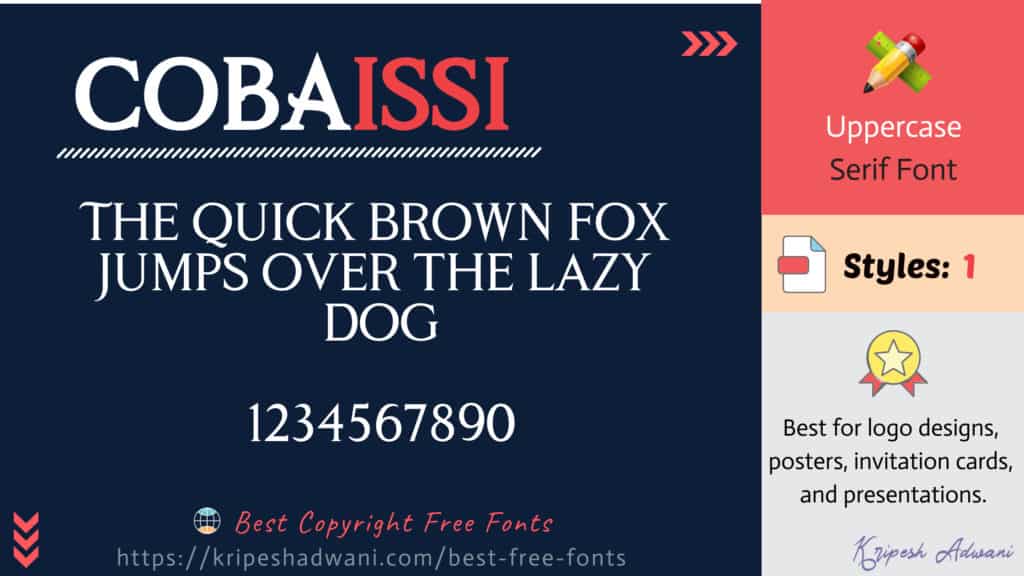
Cobaissi เป็นแบบอักษร Serif ที่สวยงามและสง่างามในอักษรตัวพิมพ์ใหญ่ที่ออกแบบโดยทีม Unblast แบบอักษรนี้แสดงถึงความมั่นใจและดูมีระดับด้วยสัมผัสที่ทันสมัย!
คุณสามารถใช้ในโครงการออกแบบต่างๆ เช่น การออกแบบโลโก้ โปสเตอร์ การนำเสนอ การ์ดเชิญ ฯลฯ
- ดีไซเนอร์ : Unblast
- รูปแบบการดาวน์โหลด : TTF และ OTF
- ฟรีสำหรับการใช้งานส่วนตัวและเชิงพาณิชย์
2. ผู้ช่วยชีวิต
ต้องการฟอนต์ที่สนุกและไร้กังวลสำหรับโปรเจกต์ของคุณใช่หรือไม่? ลองดู Life Savers แบบอักษร Slab Serif ที่เขียนด้วยลายมือที่มีกลิ่นอายขี้เล่นและขี้เล่น เหมาะที่สุดสำหรับ การโพสต์บนโซเชียลมีเดีย พาดหัวข่าวของเว็บไซต์ โบรชัวร์ ฯลฯ
- ดีไซเนอร์: Impallari Type
- 2 สไตล์
- LifeSavers Regular
- LifeSavers Bold
- รูปแบบการดาวน์โหลด : TTF
- ฟรีสำหรับการใช้งานส่วนตัวและเชิงพาณิชย์
3. เอลซี่
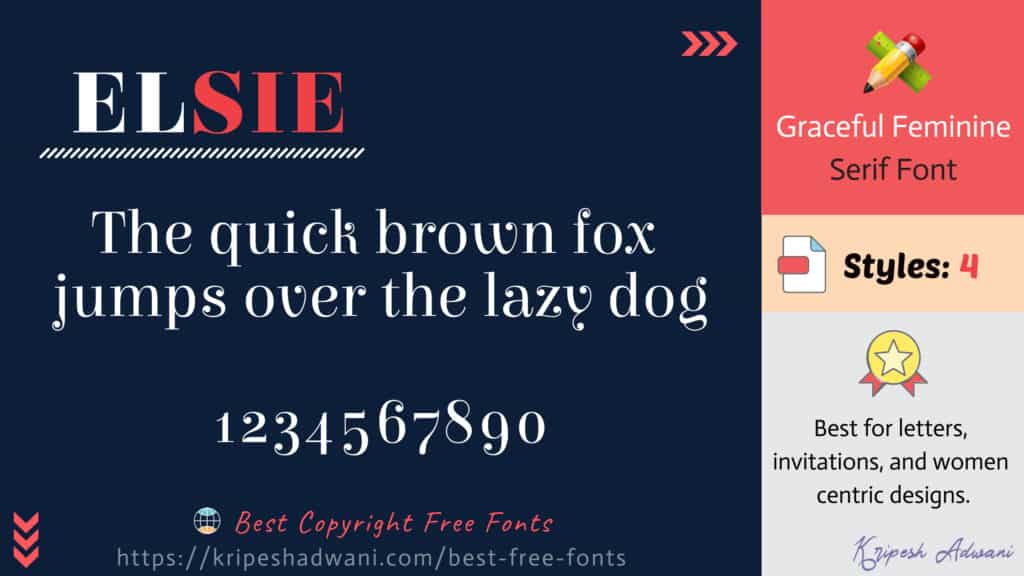
แบบอักษร Elsie ถูกออกแบบมาเพื่อเฉลิมฉลองพลังงานของผู้หญิง แบบอักษรนี้เป็นการผสมผสานระหว่างความนุ่มนวลและความแข็งแกร่ง แบบอักษรที่สง่างามนี้สามารถใช้ใน จดหมาย คำเชิญ และโครงการสร้างสรรค์ทุกประเภทที่เกี่ยวข้องกับผู้หญิง
- ดีไซเนอร์ : Alejandro Inler
- 4 สไตล์
- Elsie Regular
- หมวกแก๊ป Elsie Swash Regular
- Elsie Black
- หมวกแก๊ป Elsie Swash สีดำ
- รูปแบบการดาวน์โหลด : OTF
- ฟรีสำหรับการใช้งานส่วนตัวและเชิงพาณิชย์
4. ประทัง
Prata เป็นแบบอักษรเซอริฟที่มีความซับซ้อน ความคมชัดสูง และเซอริฟรูปสามเหลี่ยมเล็กน้อย ผสมผสานความเป็นทางการและลำลองเข้าด้วยกันอย่างลงตัว แบบอักษร Serif ฟรีนี้เหมาะสำหรับขนาดที่แสดง เช่น โฆษณา แบนเนอร์ โปสเตอร์ ฯลฯ
- ดีไซเนอร์ : Cyreal
- รูปแบบการดาวน์โหลด : TTF
- ฟรีสำหรับการใช้งานส่วนตัวและเชิงพาณิชย์
5. เมฆฝนโมโน
Nimbus Mono เป็นฟอนต์ Slab Serif แบบเว้นวรรคแบบโมโน มันดูค่อนข้างสะอาดและอ่านง่าย ซึ่งทำให้เป็นตัวเลือกที่ยอดเยี่ยมสำหรับการ แสดงข้อมูลโค้ดหรือใช้เครื่องพิมพ์ดีด ในโครงการออกแบบของคุณ
- ดีไซเนอร์ : URW Studio
- 4 สไตล์
- Nimbus Mono Regular
- Nimbus Mono Regular เฉียง
- นิมบัส โมโน โบลด์
- Nimbus Mono Bold เฉียง
- รูปแบบการดาวน์โหลด : OTF
- ฟรีสำหรับการใช้งานส่วนตัวและเชิงพาณิชย์
6. ลอรีน
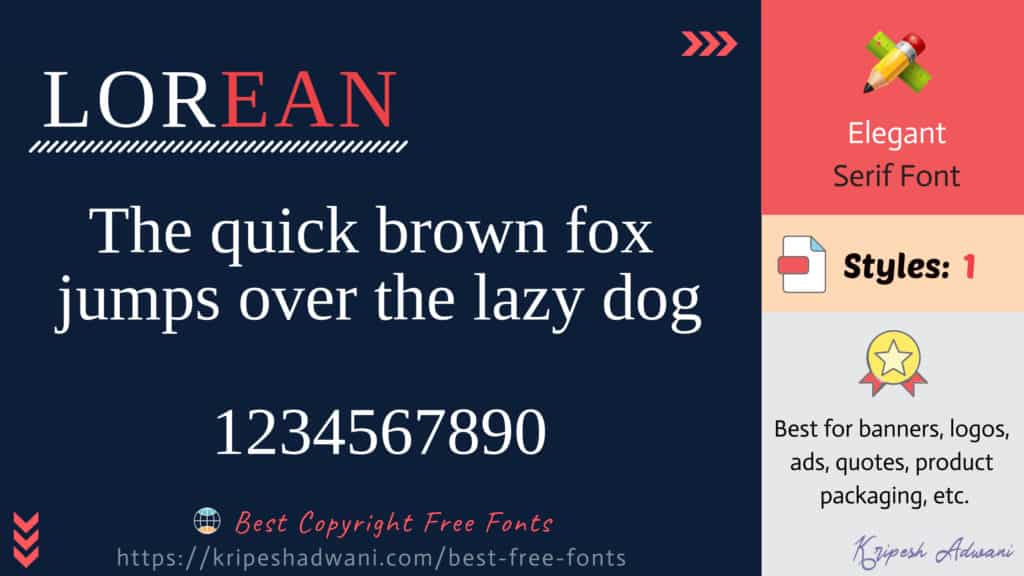
Lorean เป็นฟอนต์ serif ที่หรูหราอีกตัวหนึ่งที่มีความเปรียบต่างสูง มันเรียบง่าย สะอาด และมีพลังงานของผู้หญิงที่พูดกับจิตวิญญาณ คุณสามารถใช้สิ่งเหล่านี้บน แบนเนอร์ โลโก้ โฆษณา โพสต์โซเชียลมีเดีย คำพูด บรรจุภัณฑ์ของผลิตภัณฑ์ความงาม ฯลฯ
- ดีไซเนอร์ : ริดวาน ฟาดิละห์
- รูปแบบการดาวน์โหลด : TTF
- ฟรีสำหรับการใช้งานส่วนตัวและเชิงพาณิชย์
7. จัสตินค์
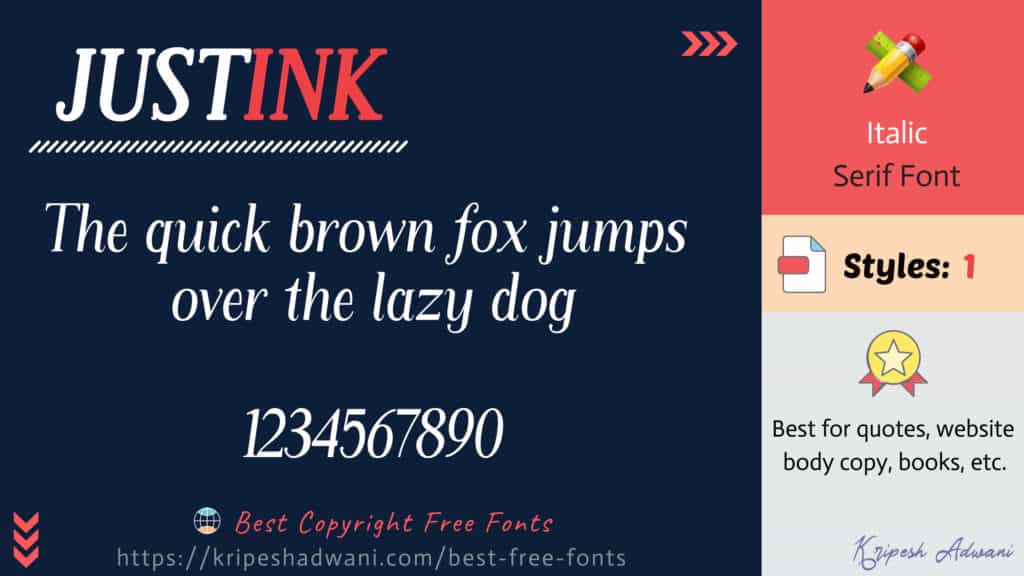
Justink เป็นฟอนต์ Serif ที่สวยงามในสไตล์ฟอนต์ตัวเอียงที่ดูน่าสนใจทีเดียว แบบอักษรนี้เหมาะที่สุดกับ กลุ่มข้อความที่ยาวกว่า เช่น หนังสือ เนื้อหาเว็บไซต์ ฯลฯ
- ดีไซเนอร์ : Amru ID
- รูปแบบการดาวน์โหลด: TTF
- ฟรีสำหรับการใช้งานส่วนตัวและเชิงพาณิชย์
8. ซินเซล
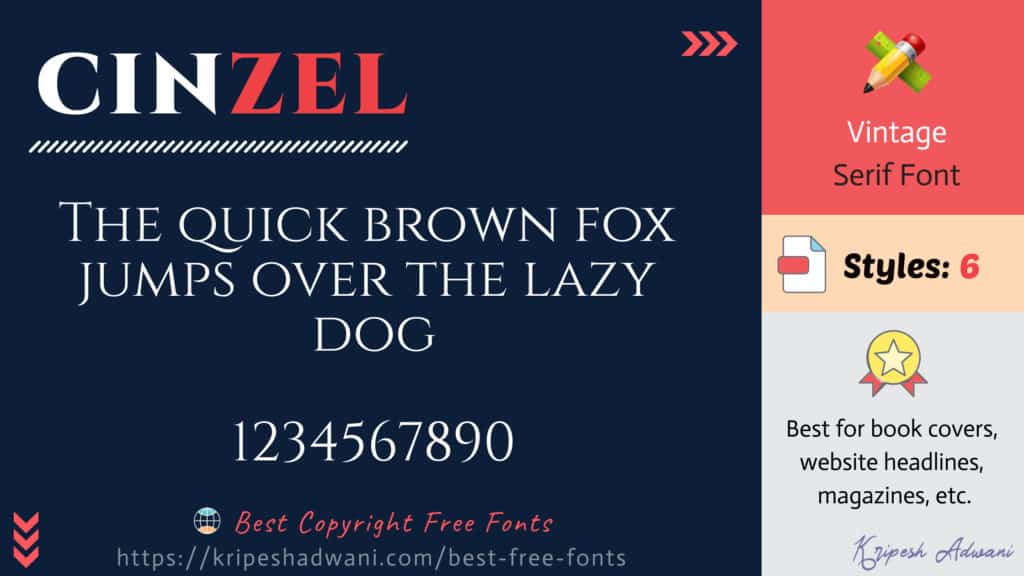
Cinzel เป็นแบบอักษร Vintage Serif ที่ได้รับแรงบันดาลใจจากจารึกโรมัน แบบอักษรนี้เป็นการผสมผสานที่ลงตัวระหว่างประวัติศาสตร์โบราณและบรรยากาศร่วมสมัย!
เหมาะที่สุดสำหรับ ปกหนังสือ พาดหัวข่าวของเว็บไซต์ นิตยสาร ฯลฯ.
- ดีไซเนอร์ : นาตานาเอล กามา
- 6 สไตล์
- ซินเซล แบล็ค
- ซินเซล โบลด์
- Cinzel Regular
- Cinzel ตกแต่งสีดำ
- Cinzel ตกแต่งตัวหนา
- Cinzel ตกแต่ง Regular
- รูปแบบการดาวน์โหลด : OTF และ TTF
- ฟรีสำหรับการใช้งานส่วนตัวและเชิงพาณิชย์
9. ชลบุรี
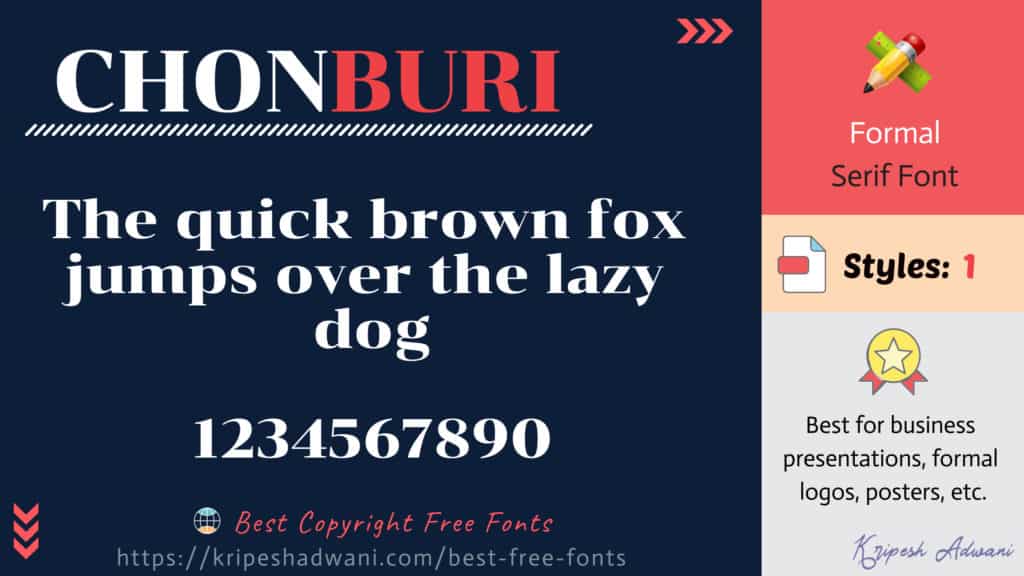
ชลบุรีเป็นฟอนต์ serif ทางการที่มีความเปรียบต่างสูง มีบรรยากาศที่ซับซ้อนซึ่งเหมาะที่สุดสำหรับ การนำเสนอทางธุรกิจ โลโก้ โปสเตอร์ และโครงการที่คล้ายคลึงกัน
- ผู้ออกแบบ: อเลฮานโดร อินเลอร์
- รูปแบบการดาวน์โหลด : OTF และ TTF
- ฟรีสำหรับการใช้งานส่วนตัวและเชิงพาณิชย์
10. โวเกอร์
Voguer เป็นฟอนต์เซอริฟคอนทราสต์สูงที่ดูทันสมัย หรูหรา และทันสมัยเป็นอย่างยิ่ง มันจะทำงานได้ดีที่สุดกับ โครงการที่เกี่ยวข้องกับแฟชั่น เช่น นิตยสารแฟชั่น การ์ดเชิญ แบนเนอร์ ฯลฯ
- ผู้ ออกแบบ : Andriy Dykun
- รูปแบบการดาวน์โหลด : TTF
- ฟรีสำหรับการใช้งานส่วนตัวและเชิงพาณิชย์
11. โบราณหมายเลข 14
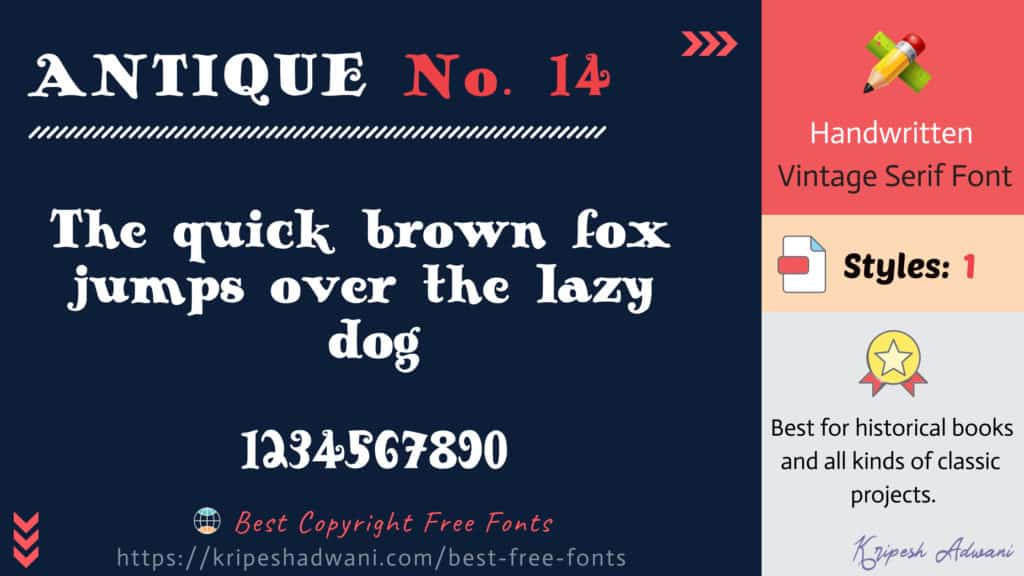
Antique No 14 เป็นฟอนต์เซอริฟโบราณในรูปแบบลายมือเขียน แบบอักษรนี้จะพาคุณย้อนเวลากลับไปในสมัยโบราณ และเหมาะอย่างยิ่งที่จะใช้ใน หนังสือประวัติศาสตร์ เป็นพาดหัว ในโครงการคลาสสิก หรืออะไรก็ได้ที่เกี่ยวข้องกับยุคเก่า
- นักออกแบบ : Typographer Mediengestaltung
- รูปแบบการดาวน์โหลด : TTF
- ฟรีสำหรับการใช้งานส่วนตัวและเชิงพาณิชย์
12. โชกะ
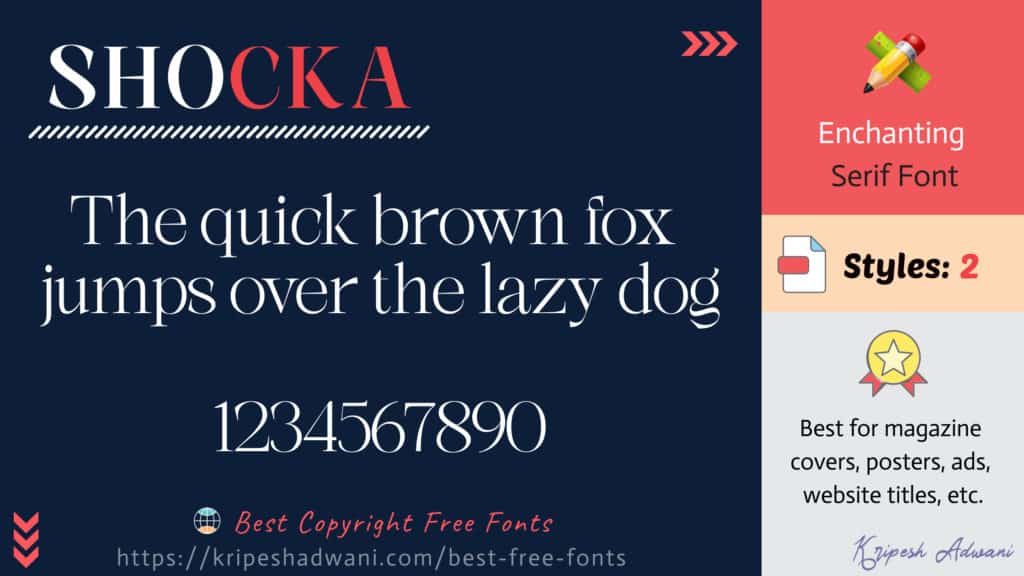
Shocka เป็นแบบอักษรเซอริฟที่มีเสน่ห์และมีเส้นโค้งเรียบ มันเรียบง่าย มีศิลปะ และสง่างาม! แบบอักษรนี้ทำงานได้ดีสำหรับโครงการออกแบบต่างๆ เช่น นิตยสาร โปสเตอร์ โฆษณา พาดหัว คำพูด โลโก้ ฯลฯ
- ดีไซเนอร์: Skinny Type
- 2 สไตล์
- Shocka Bold
- โชก้า ไลท์
- รูปแบบการดาวน์โหลด : OTF และ TTF
- ฟรีสำหรับการใช้งานส่วนตัวและเชิงพาณิชย์
13. แผ่นพื้น Permian
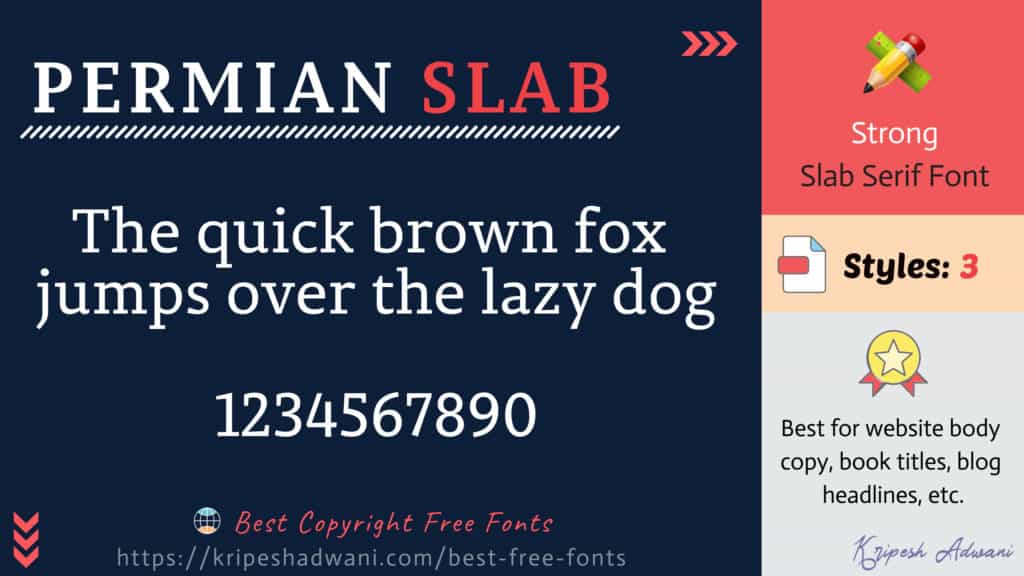
Permian Slab เป็นฟอนต์ Slab serif ที่มีลักษณะหนาและแข็งแรง มันเรียบง่าย สะอาดตา และอ่านง่าย ซึ่งทำให้เป็นตัวเลือกที่ดีสำหรับ สำเนาเนื้อหาเว็บไซต์และหนังสือ คุณยังสามารถใช้สำหรับ พาดหัว แบนเนอร์ ฯลฯ
- ดีไซเนอร์ : Permian Typeface
- 3 สไตล์
- Permian Slab Serif Regular
- Permian Slab Serif ตัวเอียง
- Permian Slab Serif Bold
- รูปแบบการดาวน์โหลด: OTF
- ฟรีสำหรับการใช้งานส่วนตัวและเชิงพาณิชย์
14. ไพ่ o
Cardo เป็นฟอนต์ Serif ยุคกลางที่ออกแบบมาสำหรับนักวิชาการ นักภาษาศาสตร์ นักคลาสสิก ฯลฯ รุ่นเก่า ฟอนต์นี้มีกลิ่นอายของประวัติศาสตร์ที่หนักหน่วง และด้วยเหตุนี้จึงเป็นตัวเลือกยอดนิยมสำหรับ โครงการออกแบบใดๆ ที่ต้องใช้ฟอนต์แบบเก่า!
- ผู้ออกแบบ : David J. Perry
- 3 สไตล์
- Cardo Regular
- คาร์โด อิตาลิก
- คาร์โด้ โบลด์
- รูปแบบการดาวน์โหลด : TTF
- ฟรีสำหรับการใช้งานส่วนตัวและเชิงพาณิชย์
ฟอนต์ Sans Serif
โดยทั่วไปแล้ว 'Sans Serif' หมายถึงไม่มี Serif แบบอักษรเหล่านี้ไม่มีโครงสร้างเหมือนเท้าที่ด้านบนและด้านล่าง ซึ่งทำให้ดูสะอาดตาและทันสมัยมากขึ้น ตัวอย่างทั่วไปของฟอนต์ Sans Serif ได้แก่ Helvetica, Arial, Roboto, Verdana เป็นต้น
ฟอนต์ Sans Serif ขึ้นชื่อเรื่อง ความเรียบง่าย เป็นมิตร และเรียบร้อย ดังนั้น คุณจึงพบว่ามีการใช้งานบนสื่อดิจิทัล เช่น สำเนาเว็บไซต์ บล็อก พาดหัว ประวัติย่อ โพสต์ในโซเชียลมีเดีย ฯลฯ
แบรนด์ชั้นนำเช่น Facebook, Google, Netflix, Microsoft, Adidas, LinkedIn ฯลฯ ใช้แบบอักษร Sans Serif ในโลโก้ของพวกเขา
แบบอักษร Sans Serif ฟรีสำหรับการใช้งานเชิงพาณิชย์
15. เบิร์กเชียร์ สวอช
Berkshire Swash เป็นฟอนต์ Sans Serif ที่สวยงามและสวยงามพร้อมลอนผมที่เรียบลื่น เหมาะสำหรับ โครงการของผู้หญิง พาดหัว แบนเนอร์ศิลปะ จดหมาย โบรชัวร์ ปกหนังสือ ฯลฯ
- ผู้ออกแบบ : Brian J. Bonislawsky
- รูปแบบการดาวน์โหลด: TTF
- ฟรีสำหรับการใช้งานส่วนตัวและเชิงพาณิชย์
16. Cal Sans
Cal Sans เป็นแบบอักษร Sans Serif ทรงเรขาคณิตที่มีรูปลักษณ์ที่สะอาดตา โดดเด่น และเรียบง่าย! มันยังใช้เป็นทางเลือกที่ดีที่สุดสำหรับฟอนต์ Futura เนื่องจากความชัดเจน Cal Sans จึงทำงานได้ดีกับทั้งโครงการขนาดเล็กและขนาดใหญ่ ตั้งแต่ สำเนาเนื้อหาเว็บไซต์ไปจนถึงแบนเนอร์และโปสเตอร์ขนาดใหญ่ !
- ผู้ออกแบบ: มาร์ค เดวิส
- รูปแบบการดาวน์โหลด : OTF
- ฟรีสำหรับการใช้งานส่วนตัวและเชิงพาณิชย์
17. หมอผี บ้า
Mad Squire เป็นฟอนต์ Sans Serif ทรงเรขาคณิตที่ได้รับแรงบันดาลใจจากเส้นคู่ขนาน มันดูค่อนข้างแปลกและมีสไตล์ ซึ่งเป็นเหตุผลว่าทำไมจึงเหมาะที่สุดสำหรับ โลโก้ พาดหัว และโครงการแสดงผลอื่นๆ
- ดีไซเนอร์ : Nele Tullus
- รูปแบบการดาวน์โหลด : TTF และ OTF
- ฟรีสำหรับการใช้งานส่วนตัวและเชิงพาณิชย์
18. Boltzz
Boltzz เป็นฟอนต์ Sans Serif ตัวพิมพ์ใหญ่ที่เป็นตัวหนาทั้งหมด ด้วยตัวหนาเป็นพิเศษ แบบอักษรนี้จึงเหมาะที่สุดสำหรับ การออกแบบ l ogo โปสเตอร์ โฆษณา พาดหัว แบนเนอร์ และอะไรก็ได้ที่สื่อถึงข้อความที่ชัดเจน !
- ผู้ออกแบบ: โนอาห์ มาร์คัส
- รูปแบบการดาวน์โหลด : TTF
- ฟรีสำหรับการใช้งานส่วนตัวและเชิงพาณิชย์
19. อาร์โรส
Arrose เป็นฟอนต์ Sans Serif ที่มีขนาดย่อพิเศษซึ่งให้บรรยากาศที่เป็นกันเองและเป็นกันเอง! เหมาะสำหรับ โปสเตอร์ภาพยนตร์ ชื่อ หัวเรื่อง และโครงการจัดแสดงอื่น ๆ ฯลฯ
- ดีไซเนอร์: GGBot
- รูปแบบการดาวน์โหลด : OTF และ TTF
- ฟรีสำหรับการใช้งานส่วนตัวและเชิงพาณิชย์
20. พิมพ์ให้ชัดเจน
พิมพ์ เห็นได้ชัดว่าเป็นแบบอักษร Sans Serif ที่ชัดเจน ทันสมัย และอ่านง่าย มันดูค่อนข้างเด็กและน่ารัก ซึ่งเป็นเหตุผลที่คุณสามารถใช้มันใน หนังสือเด็ก โปรเจ็กต์สำหรับเด็กอื่นๆ และยังเป็นสำเนาเนื้อหาบนเว็บไซต์ นิตยสาร ฯลฯ
- ดีไซเนอร์ : Blue Vinyl Fonts
- 3 สไตล์
- พิมพ์ชัดเจนปกติ
- พิมพ์ตัวหนาปกติ
- พิมพ์ประปกติ
- รูปแบบการดาวน์โหลด : OTF
- ฟรีสำหรับการใช้งานส่วนตัวและเชิงพาณิชย์
21. Apropal
Apropal คือฟอนต์แสดงผลของ Sans Serif ที่มีเอกลักษณ์เฉพาะตัวและบรรยากาศสบายๆ! เหมาะที่สุดสำหรับ ป้ายตกแต่ง หนังสือ แบนเนอร์ โฆษณา ฯลฯ.
- ผู้ออกแบบ: Rafal Buchner
- รูปแบบการดาวน์โหลด: OTF, TTF และ WOFF
- ฟรีสำหรับการใช้งานส่วนตัวและเชิงพาณิชย์
22. ซูชิซัง
Sushi Sans เป็นฟอนต์ Sans Serif แนวนีโอพิสดารที่ให้รูปลักษณ์ที่สนุกสนานและไร้กังวล เหมาะอย่างยิ่งสำหรับใช้กับ โปสเตอร์ การแสดง พาดหัว และบล็อกสั้นๆ ของเนื้อหาข้อความ
- ดีไซเนอร์ : Sushi Squad 7461
- รูปแบบการดาวน์โหลด: OTF
- ฟรีสำหรับการใช้งานส่วนตัวและเชิงพาณิชย์
23. เครื่องแต่งกาย
Outfit เป็นฟอนต์ Sans Serif ทรงเรขาคณิตซึ่งมีการออกแบบที่ค่อนข้างพิเศษและน่าดึงดูด มีให้เลือกถึง 9 สไตล์ และเหมาะอย่างยิ่งสำหรับใช้เป็น พาดหัวข่าว โฆษณา แบนเนอร์ ฯลฯ
- ผู้ ออกแบบ : โรดริโก ฟูเอนซาลิดา
- 9 สไตล์
- ชุดบาง
- เครื่องแต่งกาย Extra Light
- ชุดไฟ
- ชุดปกติ
- ชุดขนาดกลาง
- เครื่องแต่งกาย กึ่งหนา
- ชุดตัวหนา
- เครื่องแต่งกาย Extra Bold
- เครื่องแต่งกาย สีดำ
- รูปแบบการดาวน์โหลด : OTF, TTF และ WOFF2
- ฟรีสำหรับการใช้งานส่วนตัวและเชิงพาณิชย์
24. โรเซต้า
Rosseta เป็นฟอนต์แสดง Sans serif แบบวินเทจที่สวยงาม มันมีบรรยากาศของความซับซ้อนและความสง่างาม แบบอักษรนี้จะทำงานได้ดีสำหรับ พาดหัวข่าว โปสเตอร์ โลโก้แบรนด์ ฯลฯ
- ดีไซเนอร์ : Angin Studio
- รูปแบบการดาวน์โหลด: OTF และ TTF
- ฟรีสำหรับการใช้งานส่วนตัวและเชิงพาณิชย์
25. ทำงาน Sans
Work Sans เป็นฟอนต์ Sans Serif ที่ปรับให้เหมาะกับการใช้งานบนหน้าจอขนาดกลาง มันมีรูปลักษณ์ที่เรียบร้อย เรียบง่าย และทันสมัย ซึ่งทำให้ดีที่สุดสำหรับ เนื้อหาเว็บไซต์, ebooks, คำพูด, โพสต์โซเชียลมีเดีย ฯลฯ
- ผู้ออกแบบ : Wei Huang
- 18 สไตล์
- รูปแบบการดาวน์โหลด : TTF
- ฟรีสำหรับการใช้งานส่วนตัวและเชิงพาณิชย์
26. สถาปัตยกรรม
สถาปัตยกรรมคือแบบอักษรแสดงผลแบบ Sans Serif ที่ทันสมัยโดยอิงจากแบบอักษรรูปวาดต่างๆ ที่นักเรียนใช้ในโครงการออกแบบ ถ้าสังเกตดีๆ ตัวอักษรทุกตัวดูเหมือนตึก!
เป็นการผสมผสานที่ลงตัวระหว่างสไตล์วินเทจและทันสมัย ฟอนต์ Sans Serif ฟรีนี้เหมาะที่สุดสำหรับใช้ใน โลโก้ โปสเตอร์ คำพูด หัวเรื่อง โมโนแกรม ฯลฯ
- ผู้ ออกแบบ : Igor Stepanchenko
- รูปแบบการดาวน์โหลด : OTF, TTF, EOT, WOFF, HTML และ CSS
- ฟรีสำหรับการใช้งานส่วนตัวและเชิงพาณิชย์
27. อาวันติ
Avanti เป็นฟอนต์ Sans serif ทรงเรขาคณิตที่จะเพิ่มความสมบูรณ์แบบทางเรขาคณิตให้กับงานออกแบบของคุณ มันดูค่อนข้างทันสมัยและสง่างาม ซึ่งเป็นเหตุผลว่าทำไมจึงเป็นตัวเลือกที่ยอดเยี่ยมสำหรับ โครงการออกแบบกราฟิก โลโก้ เนื้อหาเว็บไซต์ ฯลฯ
- ดีไซเนอร์: Qualitype
- รูปแบบการดาวน์โหลด: OTF
- ฟรีสำหรับการใช้งานส่วนตัวและเชิงพาณิชย์
28. ชิโก
Chico เป็นฟอนต์แสดงผล Sans Serif ที่มีสไตล์ร่วมสมัย คุณสามารถใช้สำหรับ พาดหัวข่าว โปสเตอร์ โลโก้แบรนด์ ฯลฯ
- ดีไซเนอร์ : Tapiwanashe Sebastian Garikayi
- รูปแบบการดาวน์โหลด: OTF และ TTF
- ฟรีสำหรับการใช้งานส่วนตัวและเชิงพาณิชย์
แบบอักษรสคริปต์
ฟอนต์สคริปต์เป็นฟอนต์ที่ อิงจากลายมือเขียน และเลียนแบบลายเส้นที่สร้างจากข้อความที่เขียนด้วยลายมือ พวกเขามี ความสง่างาม ศิลปะ สวยงาม และมักจะเกี่ยวข้องกับ ออร่าของผู้หญิง!
ตัวอย่างทั่วไปของฟอนต์สคริปต์ ได้แก่ Brush Script MT, Edwardian Script, Lucida Handwriting, Segoe Script, Great Vibes เป็นต้น
แบบอักษรสคริปต์เหมาะที่สุดสำหรับโครงการสร้างสรรค์ทุกประเภท เช่น บัตรเชิญงานแต่งงาน ผลิตภัณฑ์ความงามและแฟชั่น สินค้าแฮนด์เมด ปกสมุด โปสเตอร์ ฯลฯ
แบรนด์ดังบางแบรนด์ที่ใช้ฟอนต์สคริปต์ ได้แก่ Instagram, Ford, Kelloggs, Cadbury, Coca Cola, Canva เป็นต้น
แบบอักษรสคริปต์ฟรีสำหรับใช้ในเชิงพาณิชย์
29. อิมพีเรียลสคริปต์
สคริปต์อิมพีเรียลเป็นอีกหนึ่งแบบอักษรลายมือที่สวยงามซึ่งสร้างขึ้นด้วยจังหวะที่สะอาดและหนักหน่วง! ประกอบด้วยอักขระละตินและยังรองรับภาษาตะวันตก กลาง และเวียดนาม
คุณสามารถใช้แบบอักษรนี้ใน ตัวอักษร แบรนด์แฟชั่น บัตรเชิญที่เป็นทางการ ผลิตภัณฑ์แฟชั่น ฯลฯ
- ผู้ ออกแบบ : Rob Leuschke
- รูปแบบการดาวน์โหลด: OTF และ TTF
- ฟรีสำหรับการใช้งานส่วนตัวและเชิงพาณิชย์
30. ขี้เหร่
Curely เป็นฟอนต์สคริปต์ที่เขียนด้วยลายมือที่น่ารักและงดงามอย่างยิ่ง ประกอบด้วยตัวพิมพ์ใหญ่และมาพร้อมกับป้ายโบนัส AI ฟอนต์นี้มีกลิ่นอายของหญิงสาว และคุณสามารถใช้มันกับ การ์ดวาเลนไทน์ หรือโปรเจกต์ออกแบบน่ารักๆ อื่นๆ ก็ได้
- ดีไซเนอร์ : Konstantine Studio
- รูปแบบการดาวน์โหลด: OTF และ TTF
- ฟรีสำหรับการใช้งานส่วนตัวและเชิงพาณิชย์
31. สวัสดีเดือนตุลาคม
Hey October เป็นฟอนต์พู่กันที่มีลายเส้นหนาและพื้นผิวที่เป็นธรรมชาติ มันให้ออร่าของความมั่นใจและความกล้าหาญ คุณสามารถใช้บน โปสเตอร์ การออกแบบเสื้อยืด คำพูด พาดหัว โซเชียลมีเดีย ฯลฯ
- ดีไซเนอร์ : Syaf Rizal
- รูปแบบการดาวน์โหลด: OTF และ TTF
- ฟรีสำหรับการใช้งานส่วนตัวและเชิงพาณิชย์
32. แซคราเมนโต
ซาคราเมนโตเป็นฟอนต์สคริปต์กึ่งเชื่อมต่อบรรทัดเดียวซึ่งอยู่ระหว่างตัวอักษรที่เป็นทางการและไม่เป็นทางการ เหมาะที่จะใช้เป็น พาดหัวและหัวเรื่องในโครงการสร้างสรรค์หรือในจดหมายและคำเชิญที่ไม่เป็นทางการ
- ดีไซเนอร์: สายตาเอียง
- รูปแบบการดาวน์โหลด: OTF และ TTF
- ฟรีสำหรับการใช้งานส่วนตัวและเชิงพาณิชย์
33. บีทติ้งวิลล์
Beattingvile เป็นแบบอักษรลายมือที่มีกลิ่นอายของวินเทจ คุณสามารถใช้มันกับ โลโก้แบรนด์ของคุณ โครงการงานฝีมือ พาดหัว ชื่อ ป้าย ฉลาก เสื้อผ้า ฯลฯ ได้อย่างง่ายดาย
- ดีไซเนอร์ : Garisman Studio
- รูปแบบการดาวน์โหลด : OTF
- ฟรีสำหรับการใช้งานส่วนตัวและเชิงพาณิชย์
34. เซลติก้า
Celtica เป็นฟอนต์แบบกอธิคที่ได้รับแรงบันดาลใจจากจารึกภาษาละตินในสมัยก่อน ฟอนต์สคริปต์ฟรีนี้เหมาะสำหรับการทำงานกับ โปรเจ็กต์การออกแบบแนวประวัติศาสตร์ และยังสามารถใช้เป็นฟอนต์ที่ดีสำหรับ หนังสือประวัติศาสตร์ หนังสือบทกวี จดหมาย ฯลฯ
- ดีไซเนอร์ : Wojciech Kalinowski
- 4 สไตล์
- หนังสือเซลติก้า
- Celtica Book Oblique
- เซลติก้า โบลด์
- Celtica Bold Oblique
- รูปแบบการดาวน์โหลด: OTF และ TTF
- ฟรีสำหรับการใช้งานส่วนตัวและเชิงพาณิชย์
35. Allura
Allura เป็นฟอนต์สไตล์การประดิษฐ์ตัวอักษรที่สง่างาม จังหวะที่ลื่นไหลของมันให้พลังงานแบบผู้หญิง และเหมาะที่สุดสำหรับ บัตรเชิญที่เป็นทางการ จดหมาย การ์ดอวยพร ผลิตภัณฑ์เพื่อความงาม ฯลฯ
- ดีไซเนอร์ : TypeSETit
- รูปแบบการดาวน์โหลด : OTF
- ฟรีสำหรับการใช้งานส่วนตัวและเชิงพาณิชย์
36. สคริปต์
Scriphy เป็นฟอนต์ลายมือที่น่ารัก ขี้เล่น และเป็นกันเอง สามารถใช้ในโครงการออกแบบต่างๆ เพื่อเพิ่มความรู้สึกส่วนตัว
ซึ่งรวมถึง จดหมาย การ์ดอวยพร บันทึกย่อ โปสเตอร์ บัตรเชิญ หนังสือ และโครงการส่วนตัวอื่น ๆ เป็นต้น
- ผู้ออกแบบ: Ala M Lockhart
- รูปแบบการดาวน์โหลด : OTF และ TTF
- ฟรีสำหรับการใช้งานส่วนตัวและเชิงพาณิชย์
37. คืนฮาโลวีน
Night Halloween เป็นแบบอักษรสคริปต์ที่น่ากลัวซึ่งออกแบบมาสำหรับวันฮาโลวีน สามารถใช้กับเสื้อเชิ้ต บัตรเชิญ ผลิตภัณฑ์ และ โปรเจ็กต์ธีมฮัลโลวีนทุกประเภทเพื่อรักษาบรรยากาศสยองขวัญ
- ดีไซเนอร์: Bluestype Studio
- รูปแบบการดาวน์โหลด: OTF และ TTF
- ฟรีสำหรับการใช้งานส่วนตัวและเชิงพาณิชย์
38. ลูกหมาพี่ เล ย์
Puppies Play เป็นฟอนต์สคริปต์ที่เล่นสนุกและเด้งดึ๋งๆ ลื่นไหลด้วยเส้นโค้งที่ลื่นไหลและมีความสุขแบบเด็กๆ! เป็นตัวเลือกที่ยอดเยี่ยมสำหรับ หนังสือนิทานสำหรับเด็ก เพลงกล่อมเด็ก คำเชิญไปงานปาร์ตี้ งานอาบน้ำเด็ก และโครงการออกแบบที่มีธีมสำหรับเด็ก!
- ผู้ ออกแบบ : Rob Leuschke
- รูปแบบการดาวน์โหลด: OTF, TTF และ WOFF2
- ฟรีสำหรับการใช้งานส่วนตัวและเชิงพาณิชย์
39. การประชุมสุดยอด
High Summit เป็นฟอนต์สคริปต์ที่เขียนด้วยลายมือในรูปแบบลายเซ็น มันมีจังหวะที่ลื่นไหลและศิลปะ แบบอักษรนี้จะโดดเด่นเมื่อใช้กับ จดหมาย คำเชิญ การ์ดอวยพร คำพูด ฯลฯ
- ผู้ออกแบบ: Alpha Beta Design Studio
- รูปแบบการดาวน์โหลด : OTF และ TTF
- ฟรีสำหรับการใช้งานส่วนตัวและเชิงพาณิชย์
40. ต้นสน
Pine Tree เป็นฟอนต์สคริปต์คัดลายมือที่หรูหรา มีสไตล์ และสวยงาม มีลายเส้นที่ตัดกันสูงที่ไหลเหมือนเนย! แบบอักษรนี้เหมาะที่สุดสำหรับ คำพูด โปสเตอร์ โพสต์บนโซเชียลมีเดีย บรรจุภัณฑ์ศิลปะ ส่วนหัวของเว็บไซต์ ฯลฯ
- ดีไซเนอร์: Kong Font Studio
- รูปแบบการดาวน์โหลด : TTF และ OTF
- ฟรีสำหรับการใช้งานส่วนตัวและเชิงพาณิชย์
41. DS Caslon Gotisch
DS Caslon Gotisch เป็นฟอนต์สคริปต์แบบเก่าและดั้งเดิมที่สามารถใช้ใน หนังสือประวัติศาสตร์และนวนิยาย ปกหนังสือ จดหมาย ฯลฯ ที่ต้องการสัมผัสแห่งยุคโบราณ!
- นักออกแบบ : Typographer Mediengestaltung
- 2 สไตล์
- DS Caslon Gotisch Regular
- DS Caslon Gotisch OsF
- รูปแบบการดาวน์โหลด: TTF
- ฟรีสำหรับการใช้งานส่วนตัวและเชิงพาณิชย์
42. รัสติลา
Raustila เป็นฟอนต์ที่เขียนด้วยลายมืออันสวยงามซึ่งมีลายเส้นที่นุ่มนวลและให้บรรยากาศที่งดงามโดยรวม เหมาะสำหรับ คำเชิญงานแต่งงาน พาดหัว การ์ดอวยพร การออกแบบเสื้อยืด ตัวอักษร ฯลฯ
- ดีไซเนอร์ : Alitdesign
- รูปแบบการดาวน์โหลด: OTF และ TTF
- ฟรีสำหรับการใช้งานส่วนตัวและเชิงพาณิชย์
แสดงแบบอักษร
แบบอักษรดิสเพลย์หรือที่เรียกว่า แบบอักษรสำหรับตกแต่ง ใช้รูปทรงและรูปแบบ ต่างๆ เพื่อ ดึงดูดความสนใจของผู้ชม
ฟอนต์เหล่านี้ ทันสมัย หนา มีเอกลักษณ์ น่าทึ่ง และเหมาะสำหรับการตั้งค่าขนาดใหญ่ เช่น พาดหัว แบนเนอร์ โปสเตอร์ โฆษณา ฯลฯ ตัวอย่างยอดนิยมของแบรนด์ที่ใช้ฟอนต์แสดงผล ได้แก่ Disney, Lego, IBM, Fanta เป็นต้น
แบบอักษรดิสเพลย์ฟรีสำหรับใช้ในเชิงพาณิชย์
43. Platonick NF
Platonick เป็นแบบอักษรตกแต่งที่ประกอบด้วยการออกแบบแบบสองบรรทัด มีลักษณะที่หรูหรา ทันสมัย และมีสไตล์ ทำให้เหมาะสำหรับ โครงการออกแบบสมัยใหม่ รวมทั้งโลโก้ โฆษณา พาดหัวข่าว ฯลฯ
- ผู้ออกแบบ : นิค เคอร์ติส
- รูปแบบการดาวน์โหลด : OTF และ TTF
- ฟรีสำหรับการใช้งานส่วนตัวและเชิงพาณิชย์
44. คาร์นิวัล เฟรคโชว์
Carnivalee Freakshow ตามชื่อที่ชัดเจนคือฟอนต์วินเทจที่มีธีมงานรื่นเริง เซอริฟแบบแหลมในแบบอักษรนี้ให้ความรู้สึกเหมือนผี เหมาะที่สุดที่จะใช้ใน ละครสัตว์ การแสดงสยองขวัญ พาดหัวข่าว ชื่อภาพยนตร์ ฯลฯ ที่ได้รับแรงบันดาลใจจากธีมสยองขวัญ
- ผู้ออกแบบ: Chris Hansen
- รูปแบบการดาวน์โหลด : TTF
- ฟรีสำหรับการใช้งานส่วนตัวและเชิงพาณิชย์
45. บอนได
Bondi เป็นฟอนต์ที่สวยงามและตกแต่งในสไตล์วินเทจ! มันดูค่อนข้างทันสมัย ดังนั้น คุณสามารถใช้มันสำหรับ โลโก้แบรนด์ ข้อความพาดหัว ชื่อเว็บไซต์ ฯลฯ
- ดีไซเนอร์ : Alejo Bergmann
- รูปแบบการดาวน์โหลด : TTF
- ฟรีสำหรับการใช้งานส่วนตัวและเชิงพาณิชย์
46. แฟนตาซีออร์
Fantazyor เป็นฟอนต์แสดงผลที่น่ารัก น่ารัก และเป็นมิตร ซึ่งใช้งานได้อย่างสมบูรณ์แบบสำหรับ หนังสือ นิตยสาร และโปรเจ็กต์ธีมเด็กทั้งหมด
- ผู้ ออกแบบ: Misha Panfilov
- รูปแบบการดาวน์โหลด : TTF, EOT, WOFF, HTML และ CSS
- ฟรีสำหรับการใช้งานส่วนตัวและเชิงพาณิชย์
47. แปลกประหลาด
Bizarre เป็นฟอนต์แสดงผลแนวสยองขวัญ ดูสูงและแคบด้วยสไตล์ย้อนยุคซึ่งเหมาะอย่างยิ่งสำหรับ ชื่อภาพยนตร์สยองขวัญ โปรเจ็กต์สยองขวัญในธีมฮัลโลวีน โปสเตอร์ พาดหัวข่าว ฯลฯ
- ดีไซเนอร์ : อังเดร รามาลโญ
- รูปแบบการดาวน์โหลด : TTF
- ฟรีสำหรับการใช้งานส่วนตัวและเชิงพาณิชย์
48. ปามิต
Pamit เป็นฟอนต์แสดงผลที่น่ารัก แปลกตา และตลก ซึ่งใช้ได้กับ ปกหนังสือ แบนเนอร์ พาดหัวข่าว โปสเตอร์ โลโก้ นิตยสาร ฯลฯ
- ผู้ ออกแบบ: Syaf Rizal
- รูปแบบการดาวน์โหลด : TTF และ OTF
- ฟรีสำหรับการใช้งานส่วนตัวและเชิงพาณิชย์
49. มัลติคัลเลอร์โปร
Multicolore Pro ตามชื่อคือฟอนต์แสดงผลหลากสีในรูปแบบ SVG มันดูน่าสนใจทีเดียว ซึ่งเป็นเหตุผลที่คุณสามารถใช้มันเพื่อ ออกแบบโลโก้และผลิตภัณฑ์ตราสินค้าอื่นๆ ของคุณได้
อย่างไรก็ตาม แบบอักษรนี้ใช้ได้กับ แอป Adobe Photoshop และ Adobe Illustrator เท่านั้น
- ดีไซเนอร์ : Evan Filipov
- รูปแบบการดาวน์โหลด : OTF
- ฟรีสำหรับการใช้งานส่วนตัวและเชิงพาณิชย์
50. ร่างห้องโดยสาร
Cabin Sketch เป็นอีกหนึ่งแบบอักษรที่สร้างสรรค์ ทันสมัย และเท่ในสไตล์วาดด้วยมือ แบบอักษรนี้เหมาะสำหรับงานออกแบบที่หลากหลาย ซึ่งรวมถึง โพสต์บนโซเชียลมีเดีย พาดหัว แบนเนอร์ โปสเตอร์ โลโก้ และอีกมากมาย!
- ดีไซเนอร์: Impallari Type
- 2 สไตล์
- ร่างห้องโดยสารปกติ
- Cabin Sketch Bold
- รูปแบบการดาวน์โหลด : OTF
- ฟรีสำหรับการใช้งานส่วนตัวและเชิงพาณิชย์
51. เคลปโต
Clepto เป็นแบบอักษรแสดงผลที่ได้รับแรงบันดาลใจจากนิยายวิทยาศาสตร์ในรูปแบบพิกเซล นอกจากนี้ยังเกี่ยวข้องกับอุตสาหกรรมเทคโนโลยีเป็นอย่างมาก แบบอักษรแสดงฟรีนี้เหมาะสำหรับ เทคโนโลยีและโลโก้ การออกแบบ และโครงการที่เกี่ยวข้องกับการเข้ารหัสลับ
- ผู้ ออกแบบ: Hazral Aswad
- รูปแบบการดาวน์โหลด : OTF และ TTF
- ฟรีสำหรับการใช้งานส่วนตัวและเชิงพาณิชย์
52. พีช Sundress
Peach Sundress เป็นฟอนต์แบบ bi-linear ที่โค้งมน โค้งมน และมีสไตล์เป็นตัวเขียน เหมาะที่สุดสำหรับการแสดง ข้อความและพาดหัวข่าว โปสเตอร์ แบนเนอร์ และโครงการอื่นๆ ที่ไม่เป็นทางการแต่เป็นศิลปะ!
- ดีไซเนอร์ : Teagan White
- รูปแบบการดาวน์โหลด: TTF
- ฟรีสำหรับการใช้งานส่วนตัวและเชิงพาณิชย์
53. กลูเตน
Gluten เป็นฟอนต์แสดงผลที่น่ารัก ตลก และขี้เล่น เหมาะสำหรับ เกมสำหรับเด็ก การ์ตูน งานฝีมือ และผลิตภัณฑ์สำหรับเด็กอื่นๆ
- ผู้ออกแบบ : Tyler Finck
- 27 สไตล์
- รูปแบบการดาวน์โหลด : OTF และ TTF
- ฟรีสำหรับการใช้งานส่วนตัวและเชิงพาณิชย์
54. Klaxons
Klaxons เป็นแบบอักษรแสดงผลที่มีเอกลักษณ์ซึ่งได้รับอิทธิพลจากสไตล์นีออน แบบอักษรนี้ใช้ได้ดีกับ โปสเตอร์ แบนเนอร์ ใบปลิว โฆษณา พาดหัวข่าว โซเชียลมีเดีย ศิลปะ ฯลฯ
- ดีไซเนอร์ : มาร์ค ไวท์
- รูปแบบการดาวน์โหลด : OTF
- ฟรีสำหรับการใช้งานส่วนตัวและเชิงพาณิชย์
55. มาเจล
Magiel เป็นแบบอักษรแสดงทางเรขาคณิตที่มีกลิ่นอายของตัวหนาและตลก! มันจะทำงานได้ดีกับ โครงการสมัยใหม่ทุกประเภทรวมถึงโลโก้ โปสเตอร์ ชื่อ ฯลฯ
- ดีไซเนอร์ : Mateusz Machalski
- รูปแบบการดาวน์โหลด : OTF, TTF และ WOFF
- ฟรีสำหรับการใช้งานส่วนตัวและเชิงพาณิชย์
56. กาแล็กซี่
กาแล็กซี่เป็นแบบอักษรที่แสดงอนาคตในตัวอักษรบล็อกและมีรูปแบบทางเรขาคณิต เหมาะสำหรับ โลโก้ โครงการในธีมอวกาศ โปสเตอร์ แบนเนอร์ และโครงการสร้างสรรค์อื่นๆ
- ผู้ออกแบบ : Dmitri Baranov
- รูปแบบการดาวน์โหลด : OTF
- ฟรีสำหรับการใช้งานส่วนตัวและเชิงพาณิชย์
57. รูปร่างเอเชีย
AsianShape เป็นฟอนต์แสดงผลที่ได้แรงบันดาลใจจากตัวละครเอเชียและดูเหมือนการ์ตูนเล็กน้อย! มีรูปลักษณ์ที่สะอาดตาและสนุกสนาน เหมาะสำหรับ โปสเตอร์ แบนเนอร์ พาดหัวนิตยสาร โลโก้ ฯลฯ
- ดีไซเนอร์ : Lucas Ferreira